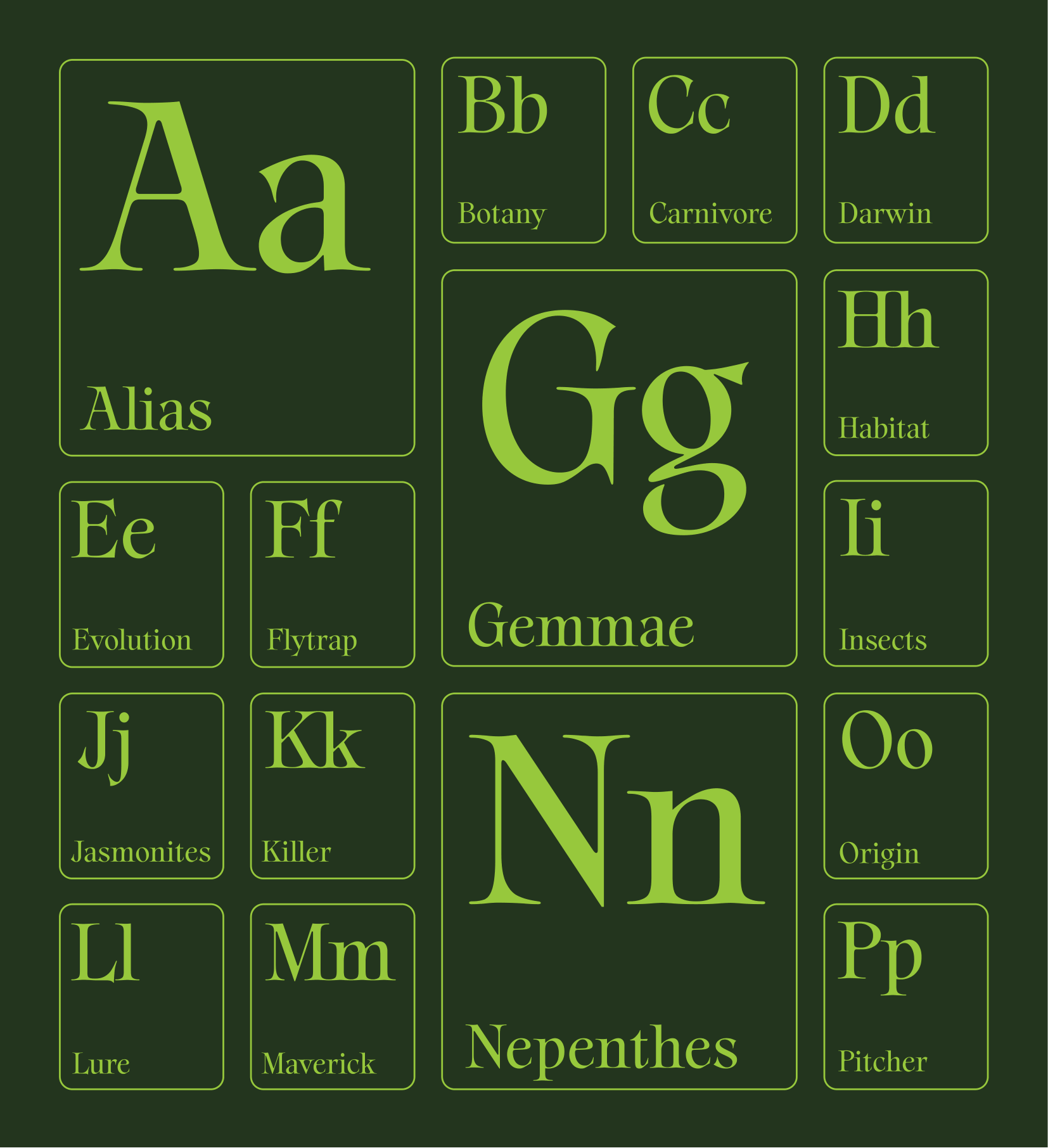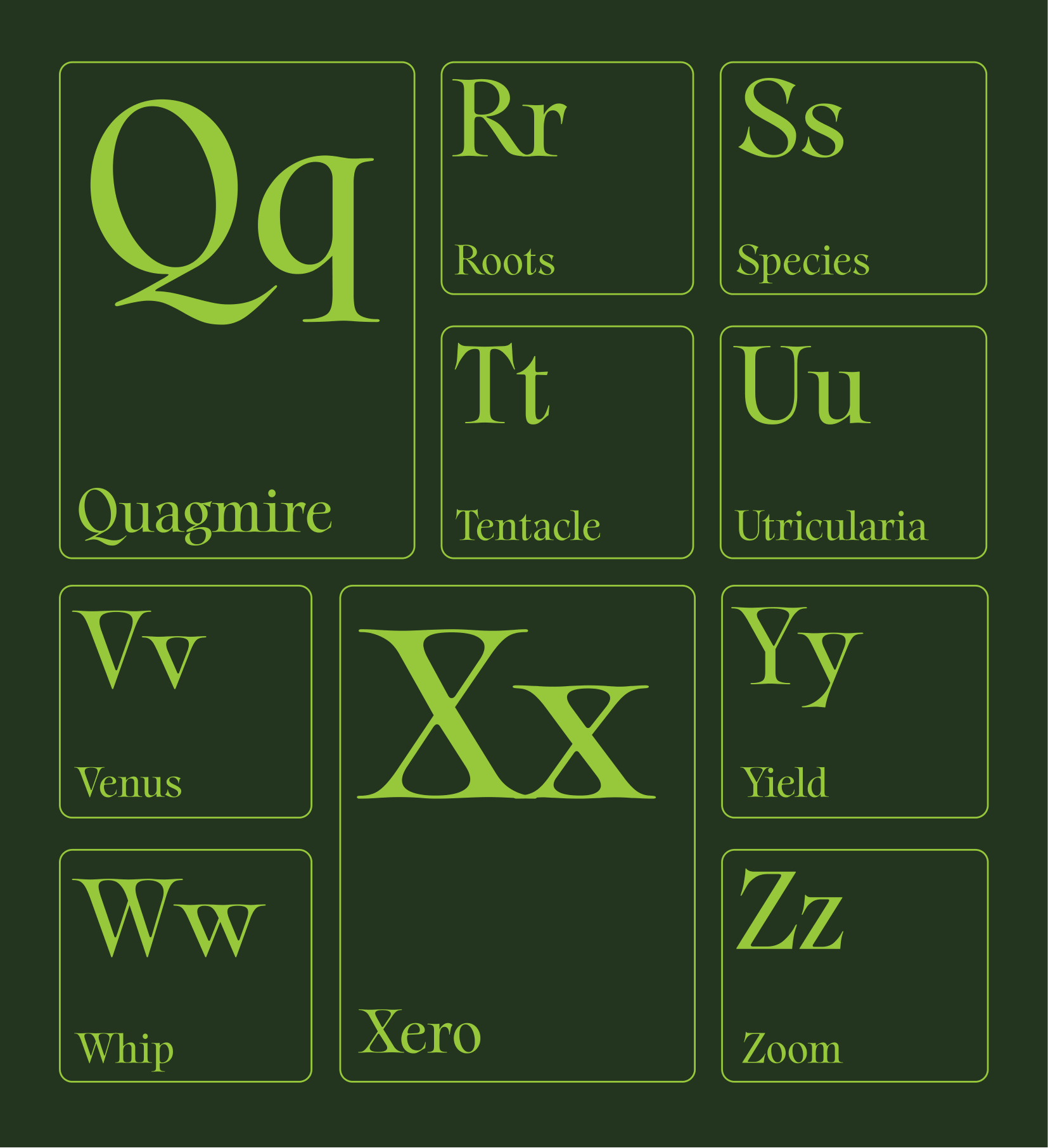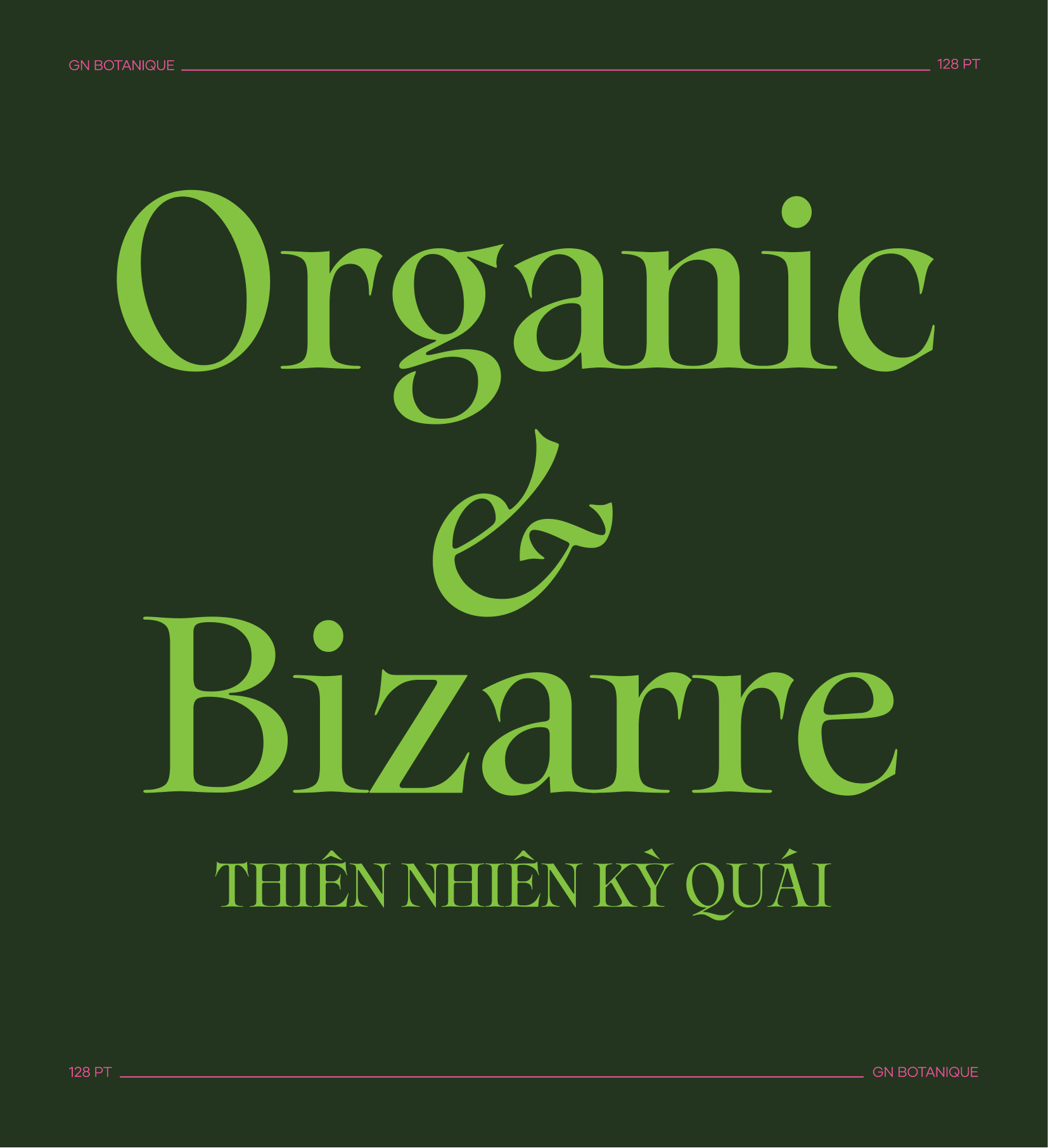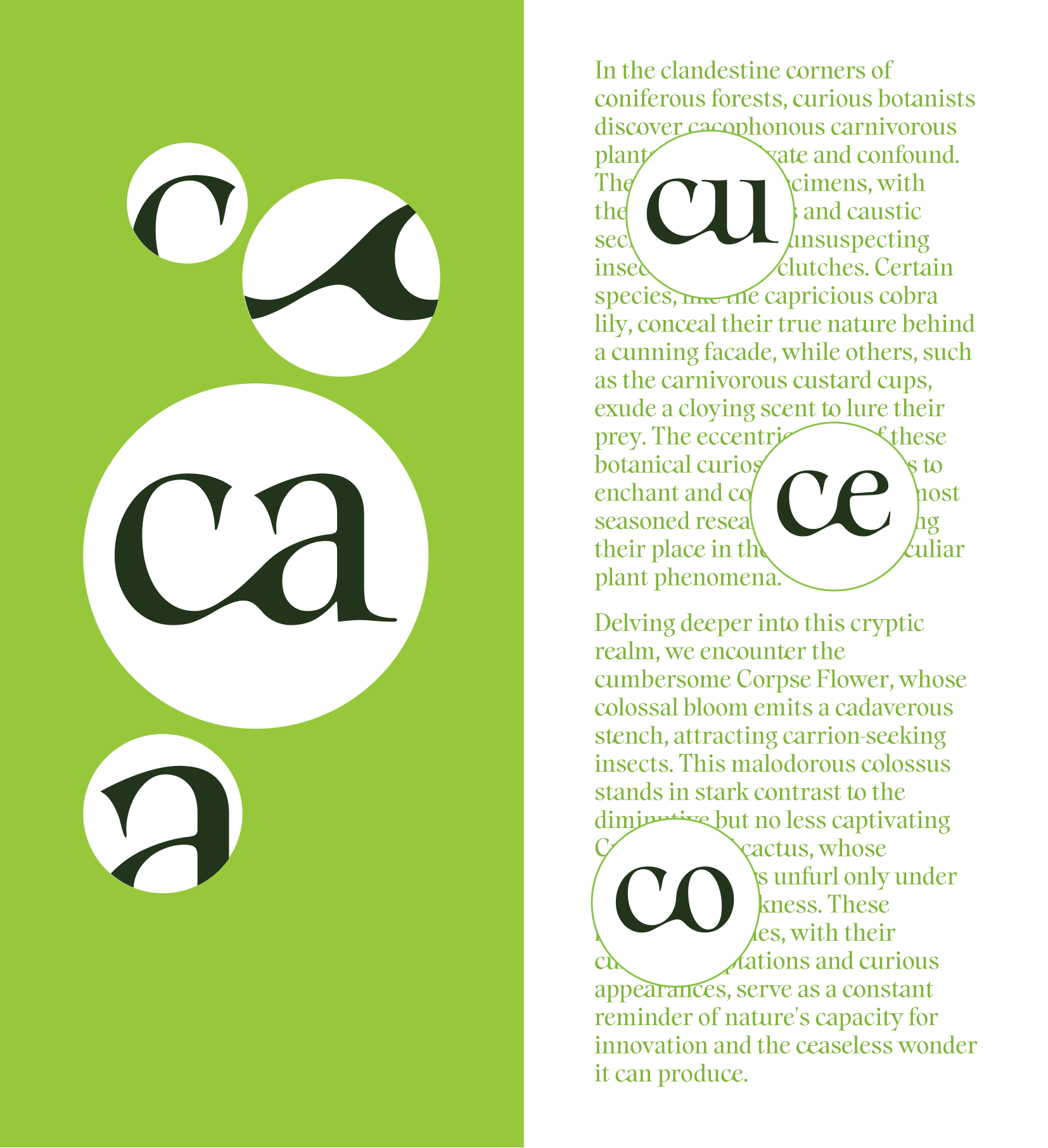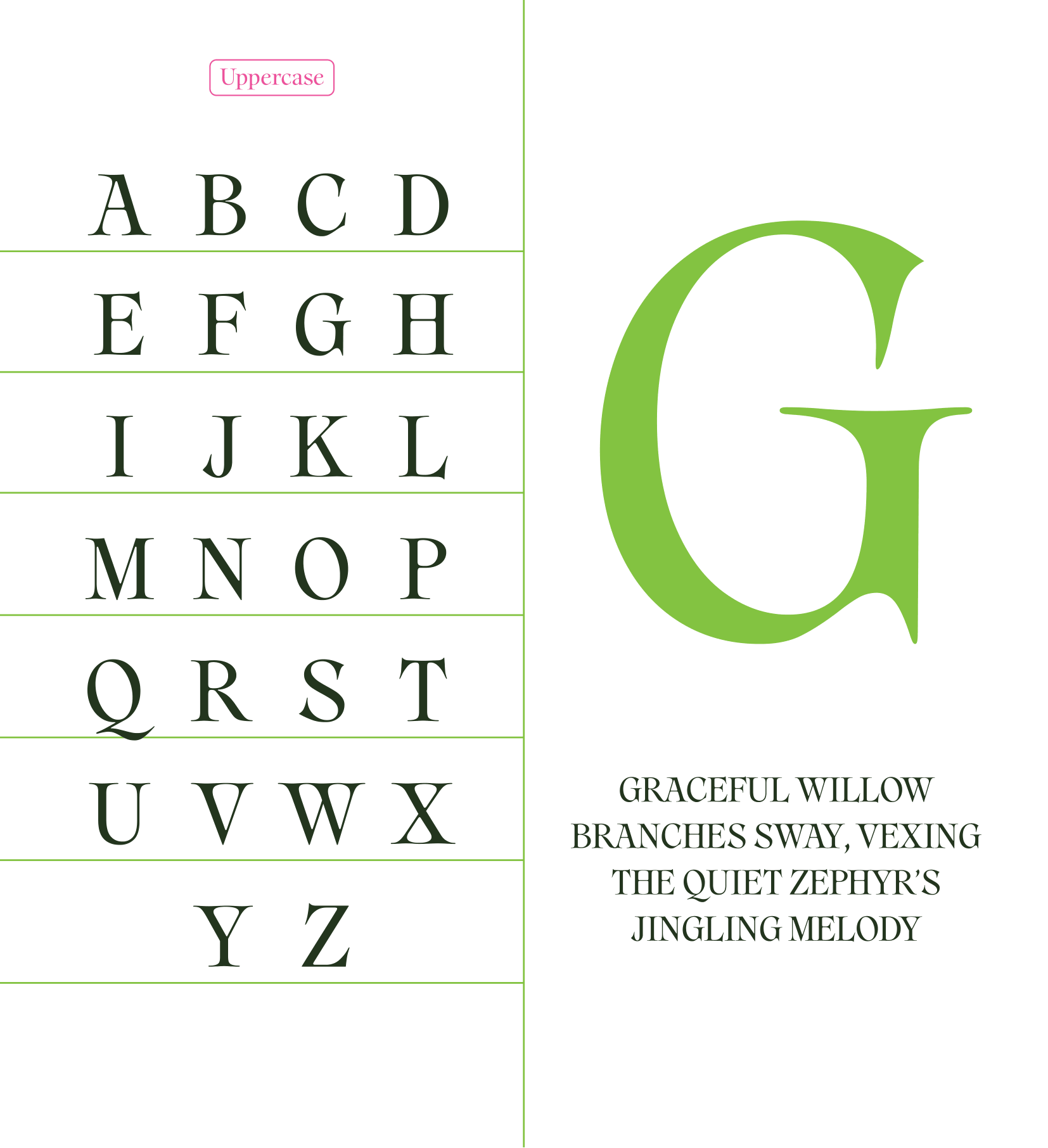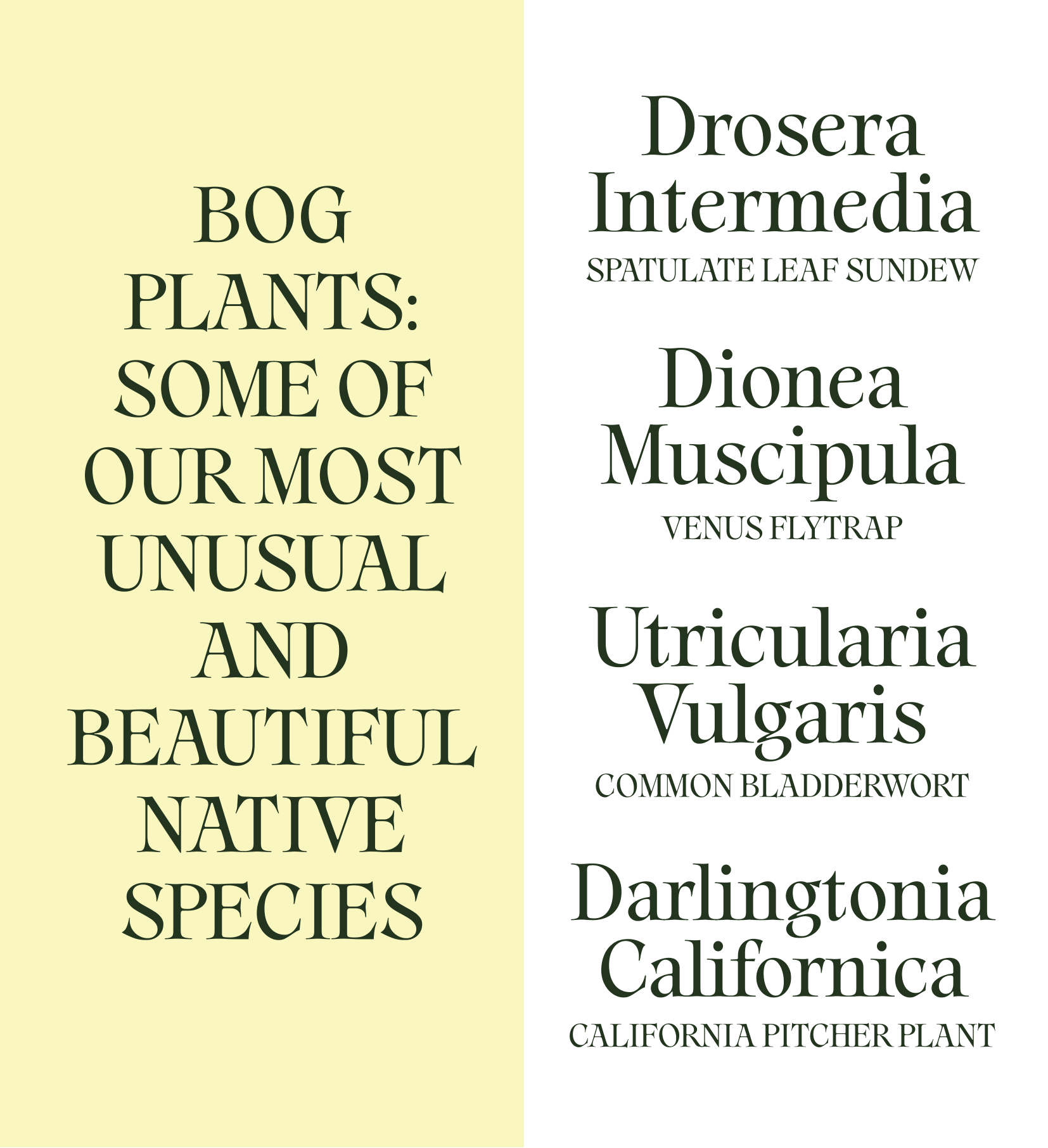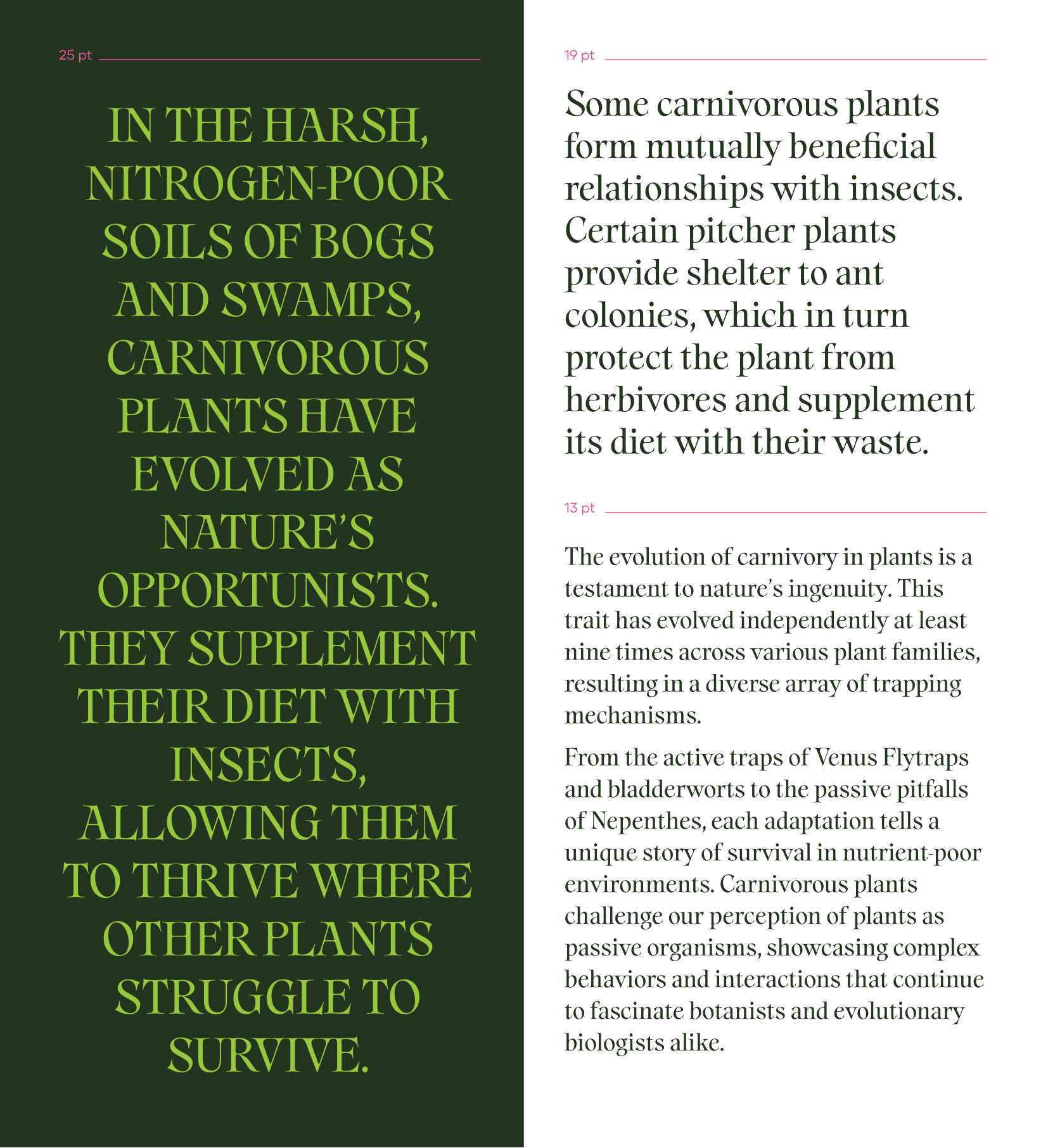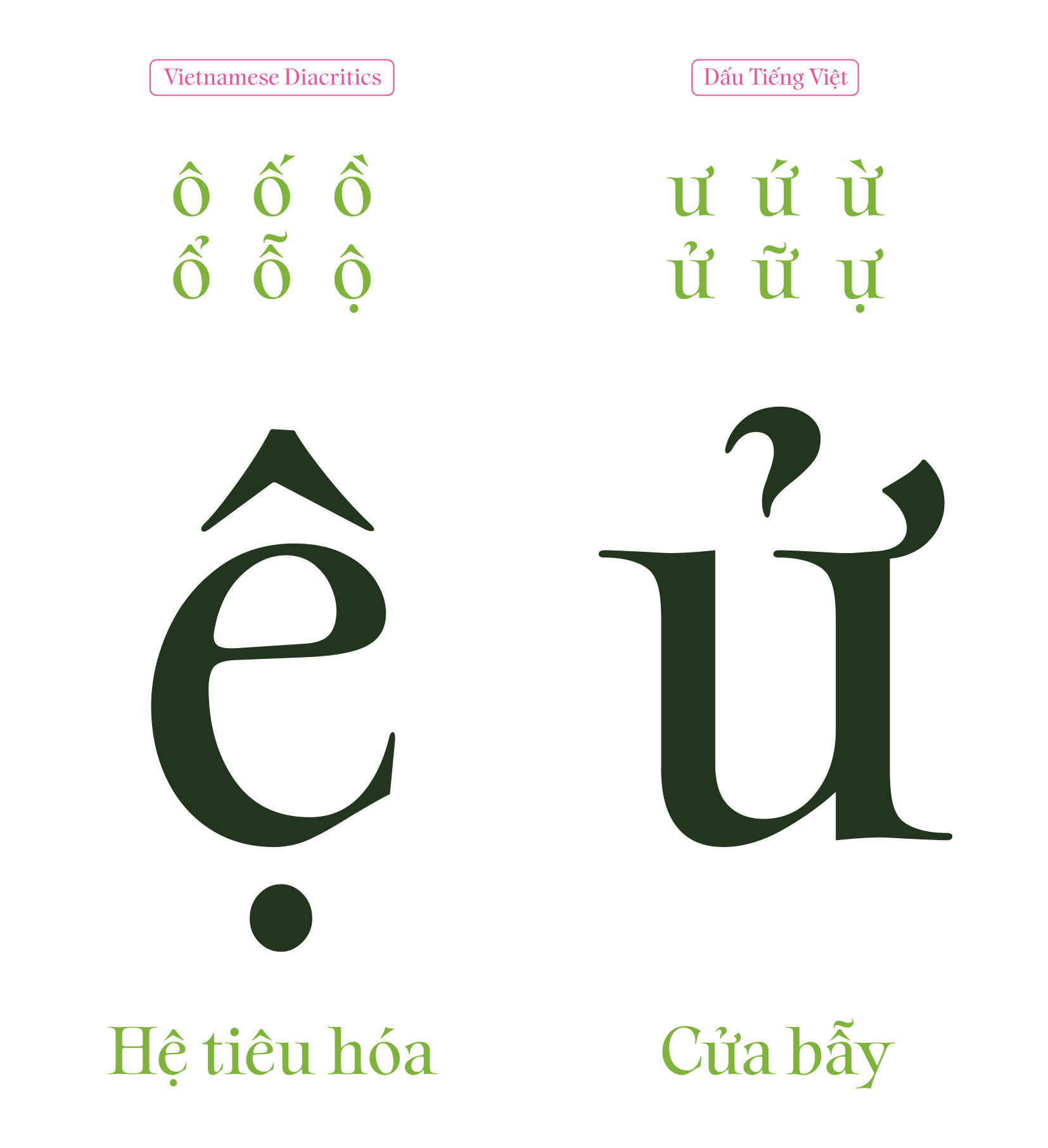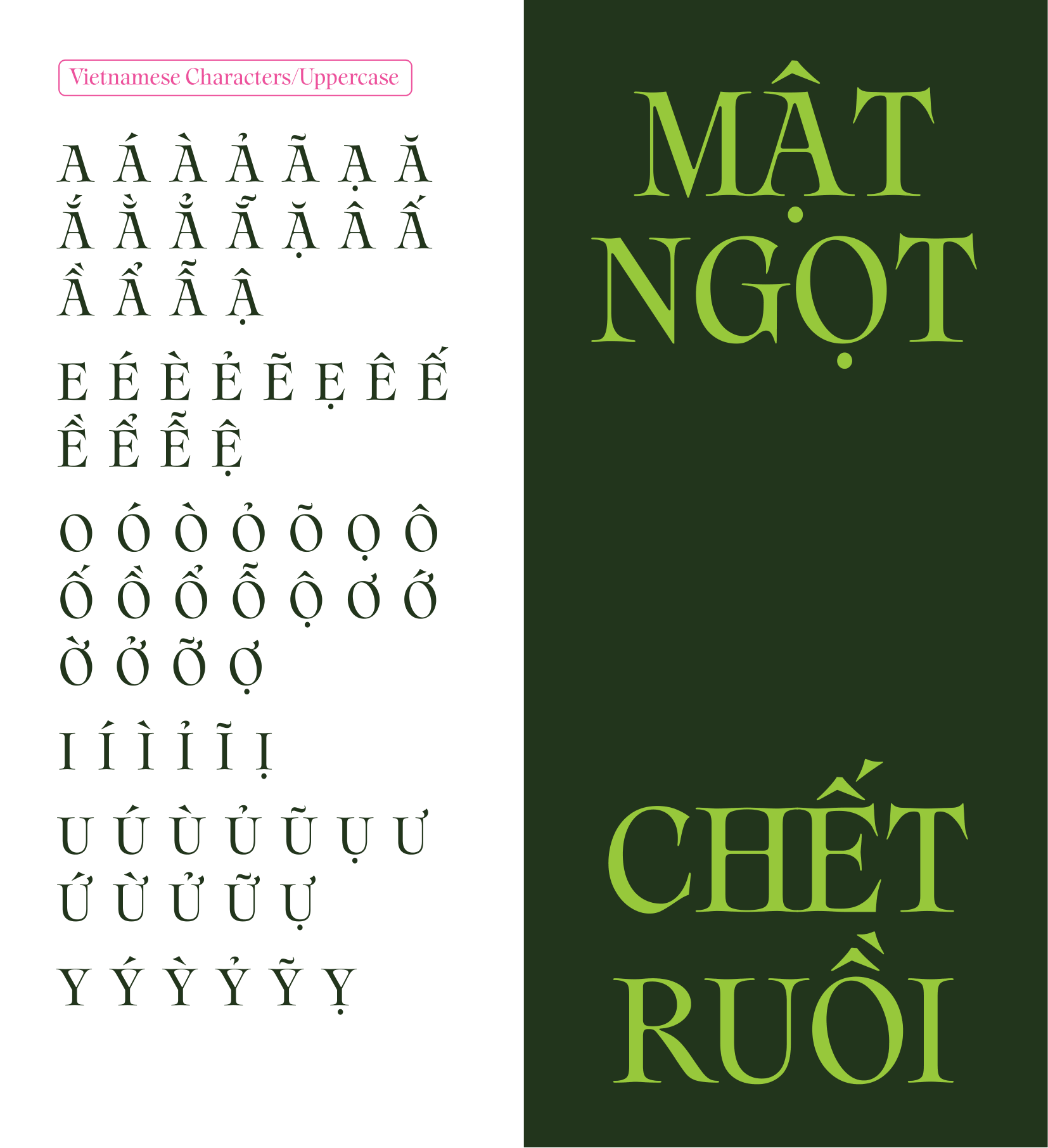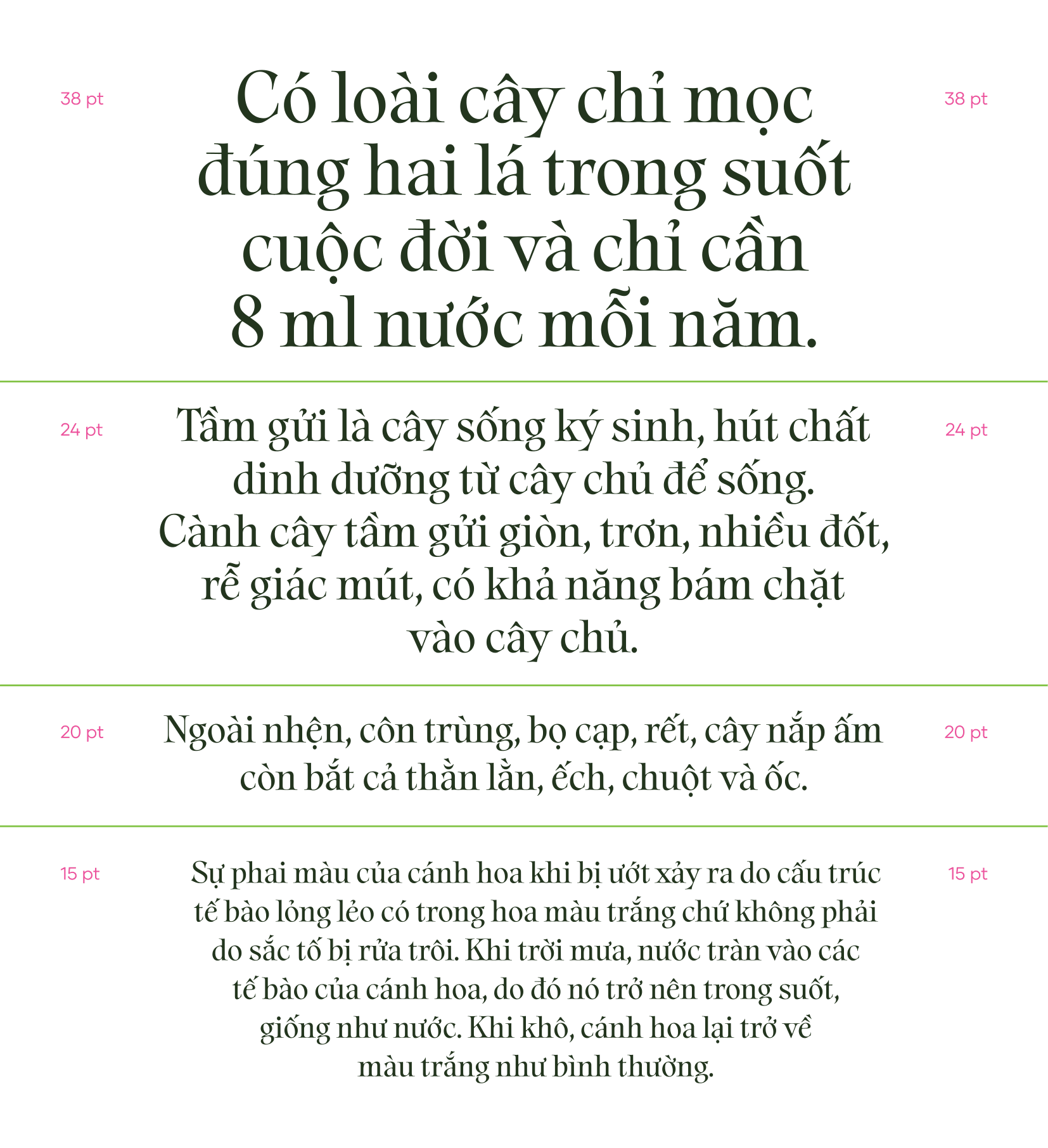
GN Botanique
Về GN Botanique: GN Botanique là một font chữ serif display ấn tượng, lấy cảm hứng từ thế giới kỳ bí của những loài thực vật ăn thịt và ký sinh. Những hình dạng sắc bén, hữu cơ cùng những chân chữ kéo dài gợi lên hình ảnh của các tua cuốn, bẫy và vòi hút của những mẫu thực vật phi thường này. Kiểu chữ tạo ra một sức căng thị giác đầy mê hoặc, hòa quyện giữa sự thanh lịch với vẻ quyến rũ rùng rợn của những loài thực vật kỳ lạ nhất trong tự nhiên.
GN Botanique
Organic & Bizarre
GN Botanique
Cây ăn thịt
GN Botanique
Thiên nhiên kỳ quái
GN Botanique
Trong thế giới thực vật đầy bí ẩn, cây ăn thịt (thực vật ăn thịt) là những sinh vật kỳ diệu đã tiến hóa để săn mồi thay vì chỉ hấp thụ chất dinh dưỡng từ đất.
GN Botanique
They do not eat people in the literal sense, though human imagination has long spun legends of "man-eating plants" in literature and cinema, but some larger species such as Nepenthes rajah are capable of digesting small mice, lizards, and even small birds that fall into their traps. This is precisely why they are simultaneously fascinating and spine-chilling, the beauty of nature concealing within itself a deadly trap. The world of carnivorous plants is a reminder that evolution has no limits when survival is at stake, producing some of the most theatrical and bizarre life forms our planet has ever seen.